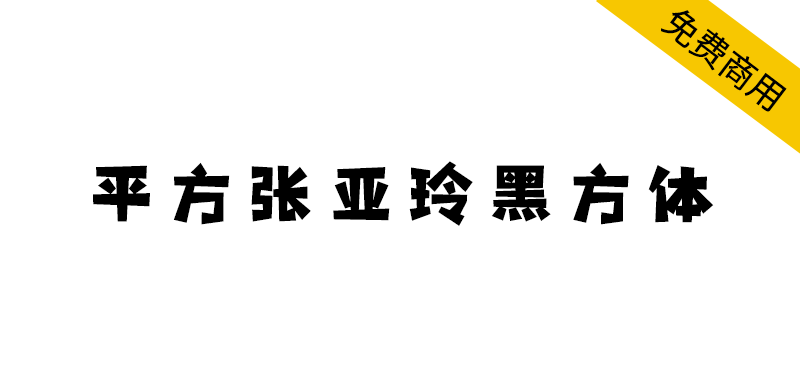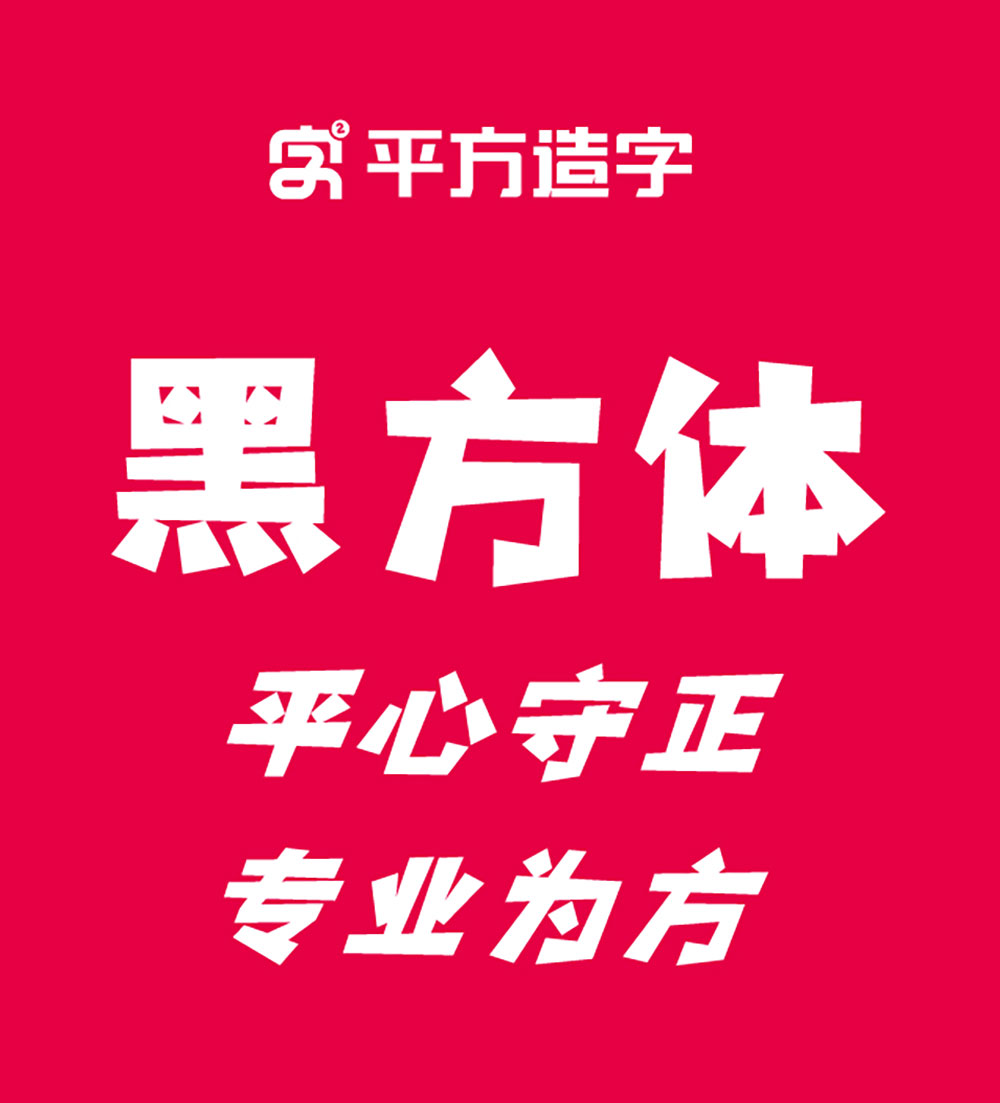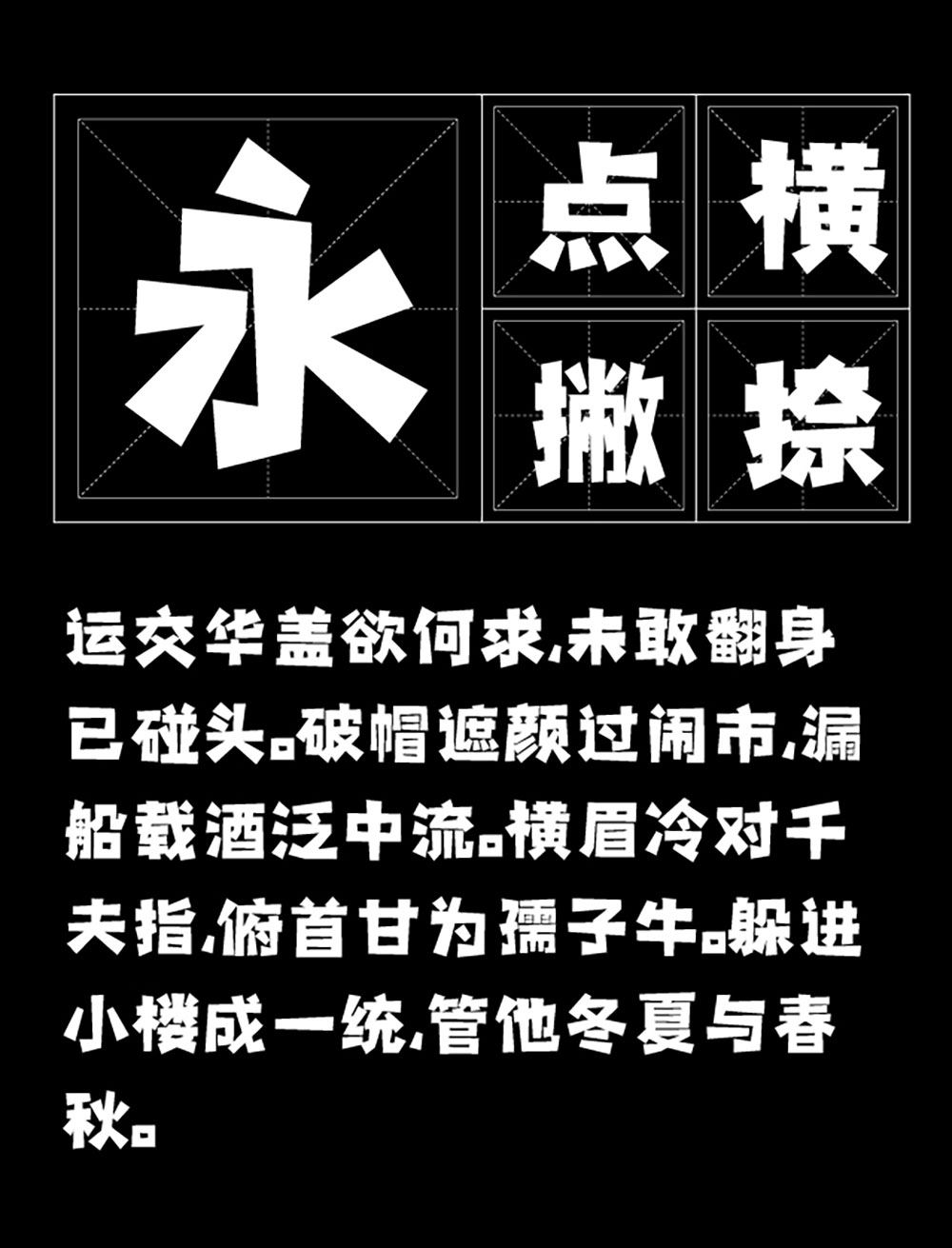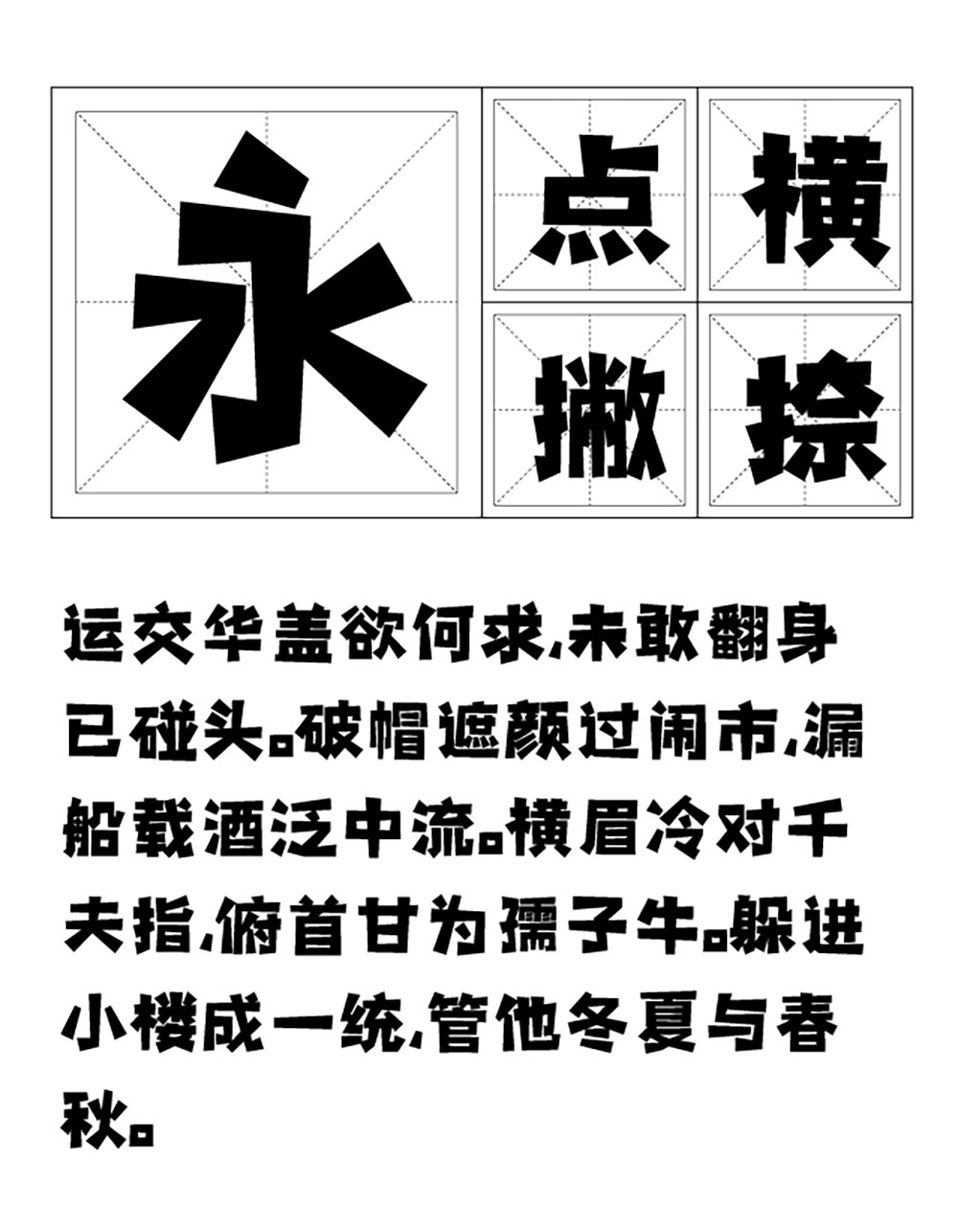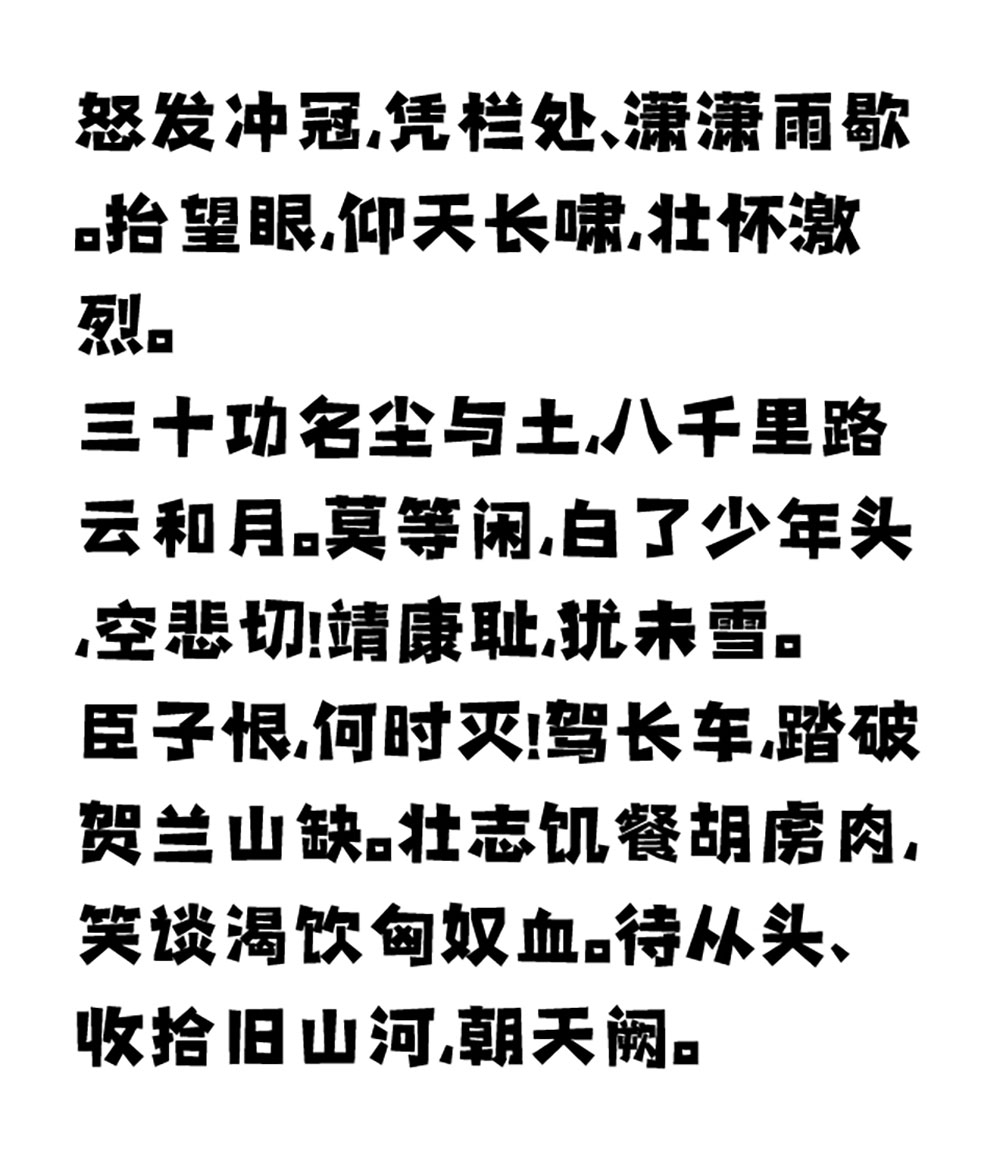
平方张亚玲黑方体是一款专为艺术广告设计打造的创意字体,该字体巧妙融合了黑体的结构特点与卡通的活泼特质,在保持黑体基本特征的同时,注入了生动有趣的视觉元素,使整体风格兼具专业性与趣味性。
平方张亚玲黑方体由字体设计师张亚玲所创作,字体为现代设计艺术体,特点简约时尚适用于多种场合,内容为中文简体字库。字体采用OpenType格式,基于中华人民共和国GB2312-80字符集标准,共收容字数6763汉字,常用标点符号123个,共计字符6886个。